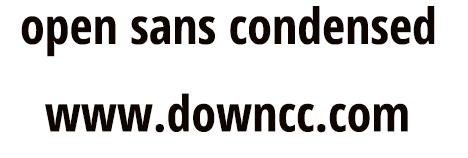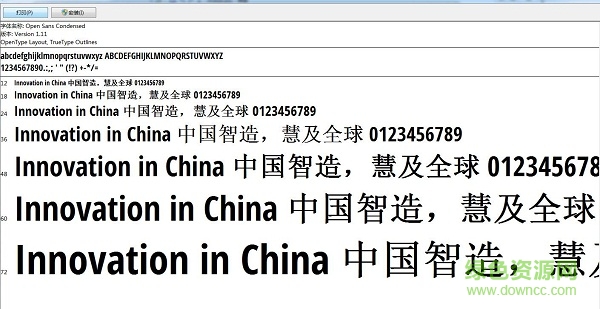
open sans condensed字體包收錄了 light和 bold兩種字型,線條粗,字距緊湊,具有力量感,結(jié)構(gòu)堅(jiān)實(shí),布局嚴(yán)謹(jǐn),適用于報(bào)紙、期刊中的大標(biāo)題,有需要者歡迎在綠色資源網(wǎng)免費(fèi)下載!